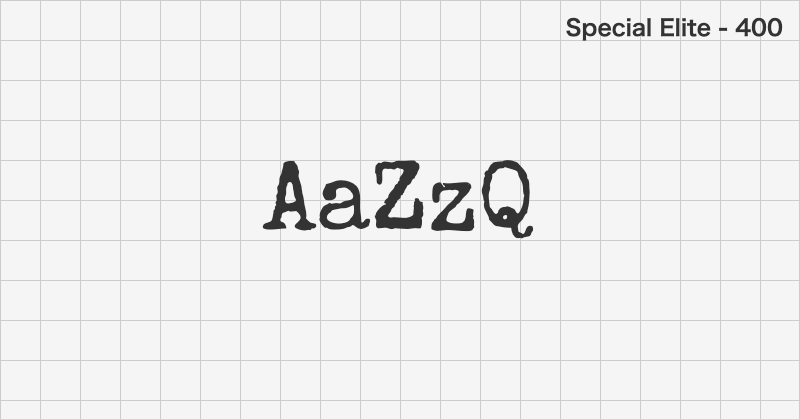
Special Elite は、タイプライターの文字を模したフォントで、レトロな印象を持っています。特に、タイプライターの特有の質感を再現することに重点を置いています。
Special Elite は、アメリカ・シカゴを拠点とするタイプファウンドリー Astigmatic によってデザインされ、古いタイプライターのスタイルを再現することを目的としています。レトロな雰囲気が、さまざまなデザインプロジェクトに適しています。